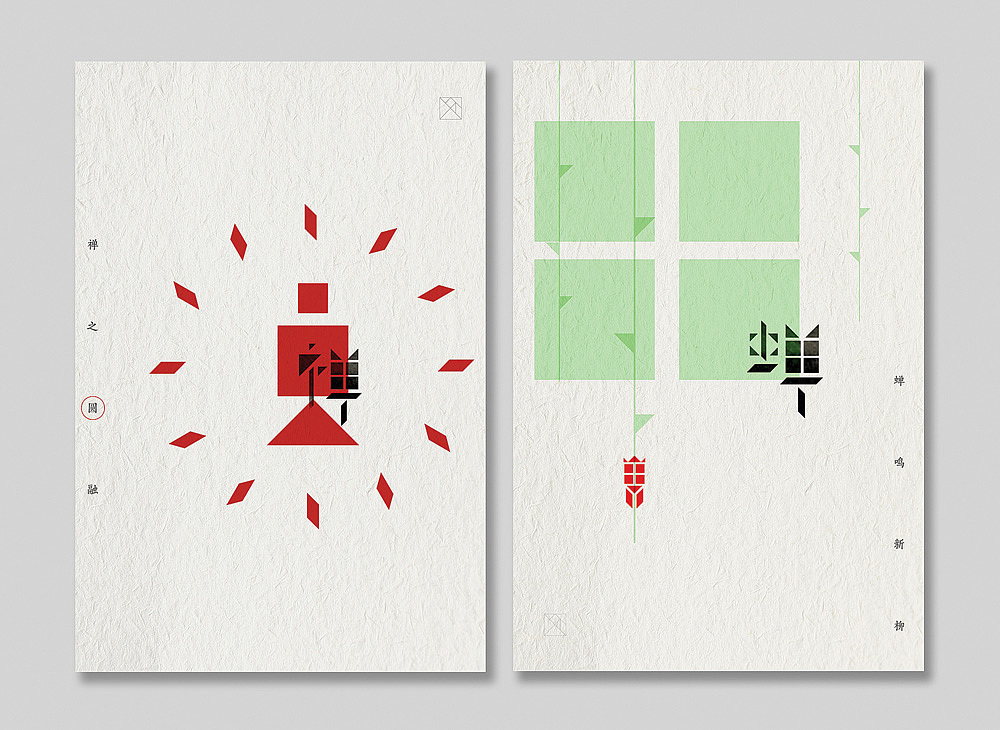
弄巧成拙 汉字实验
Experimental Heyes Design Studio 2013 font creation : font creation inspired by Zhao Zhijian calligraphy spelling puzzle , with the most simple geometry deconstruction characters, fun fun , humble interesting phenomena ! It called " self-defeating body font " it ! Font Poster Test : This is a cicada wing family hermit , a kind of " where the dust alight ." Awareness . Cicada is also a Zen .
何视设计工作室2013字体实验创作: 字体创作启发于赵之谦的七巧板拼字书法,用最简单的几何图形解构汉字,好玩趣味,拙趣横生!就取名“弄巧成拙体”吧!字体海报试验:蝉该是翅族的隐士,一种“何处惹尘埃”的了悟。蝉亦是禅。